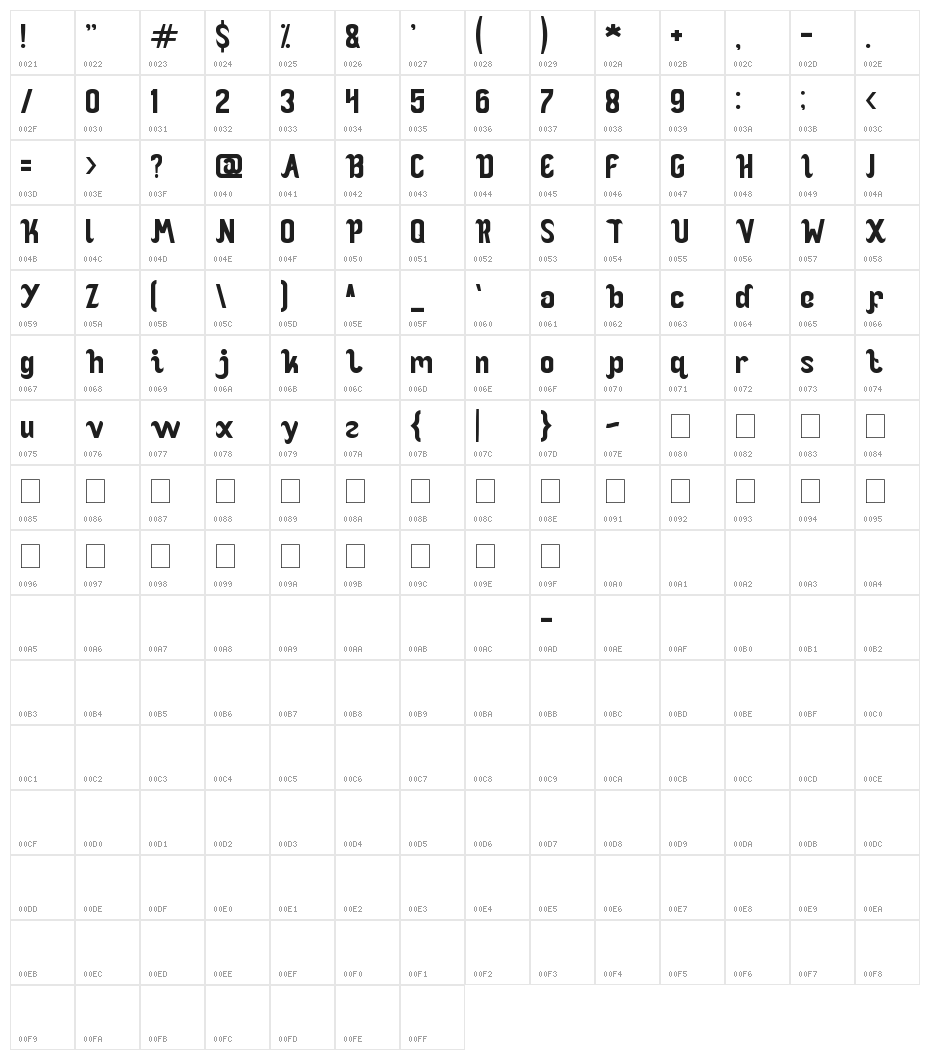
OCEAN Font
| Общий стиль | Playful, Retro-Modern |
| Рекомендуемые проекты | Ideal for children's books, playful branding, posters, and creative advertising campaigns. |